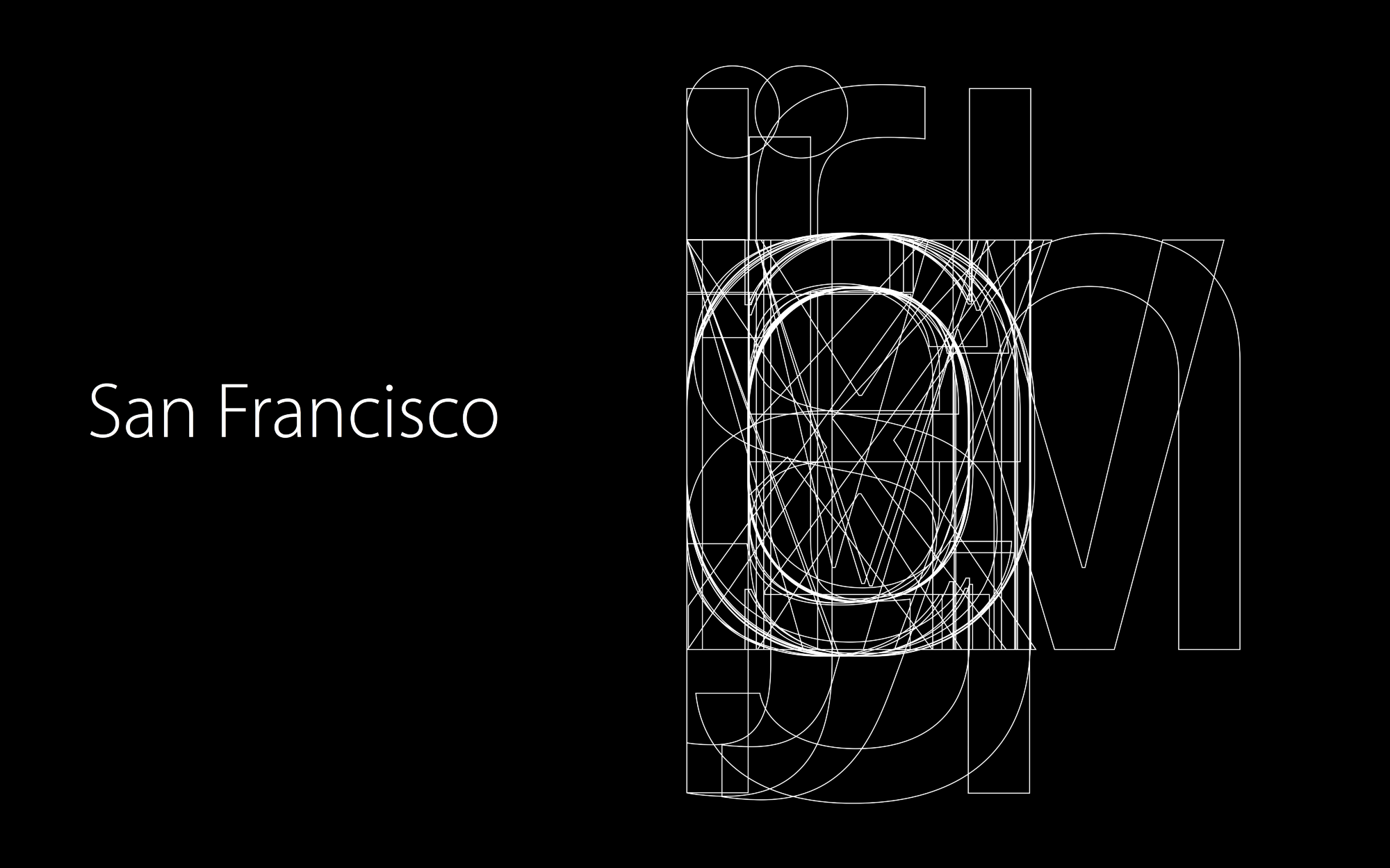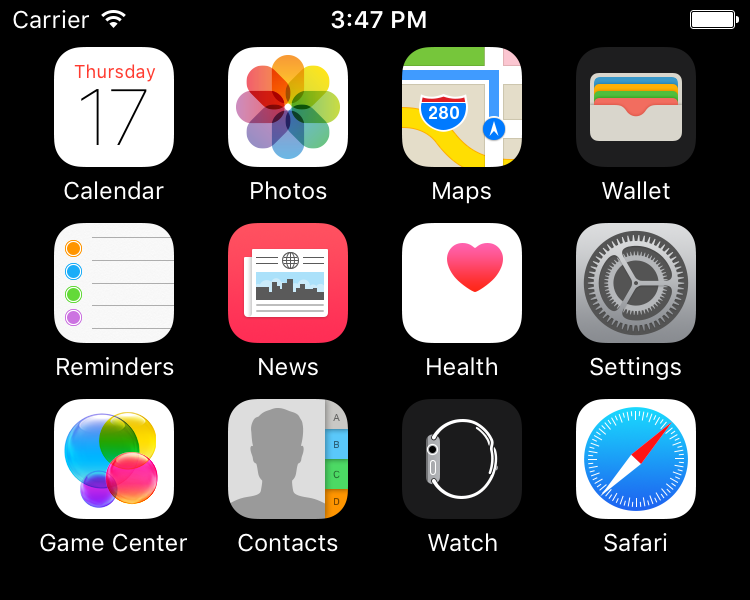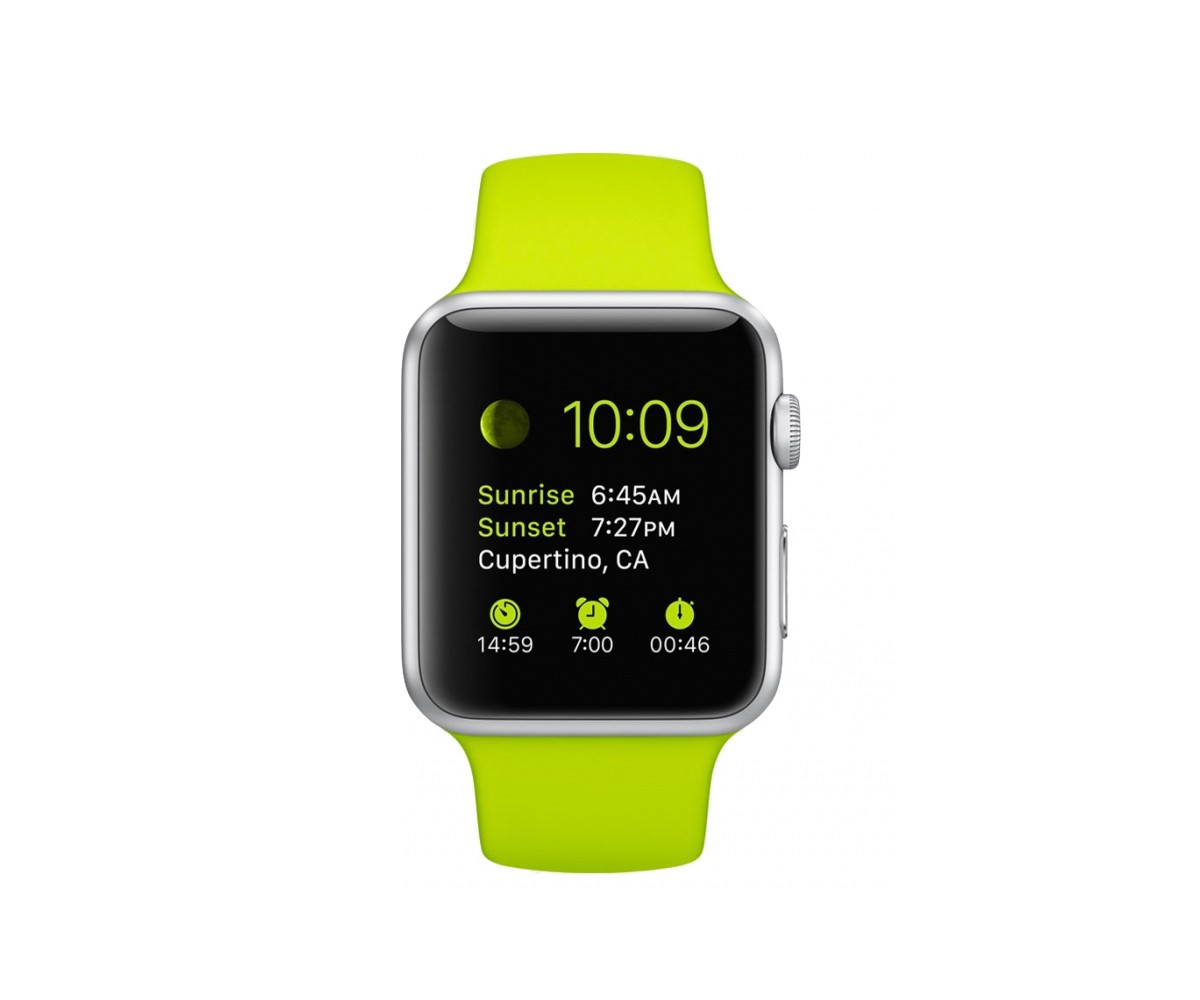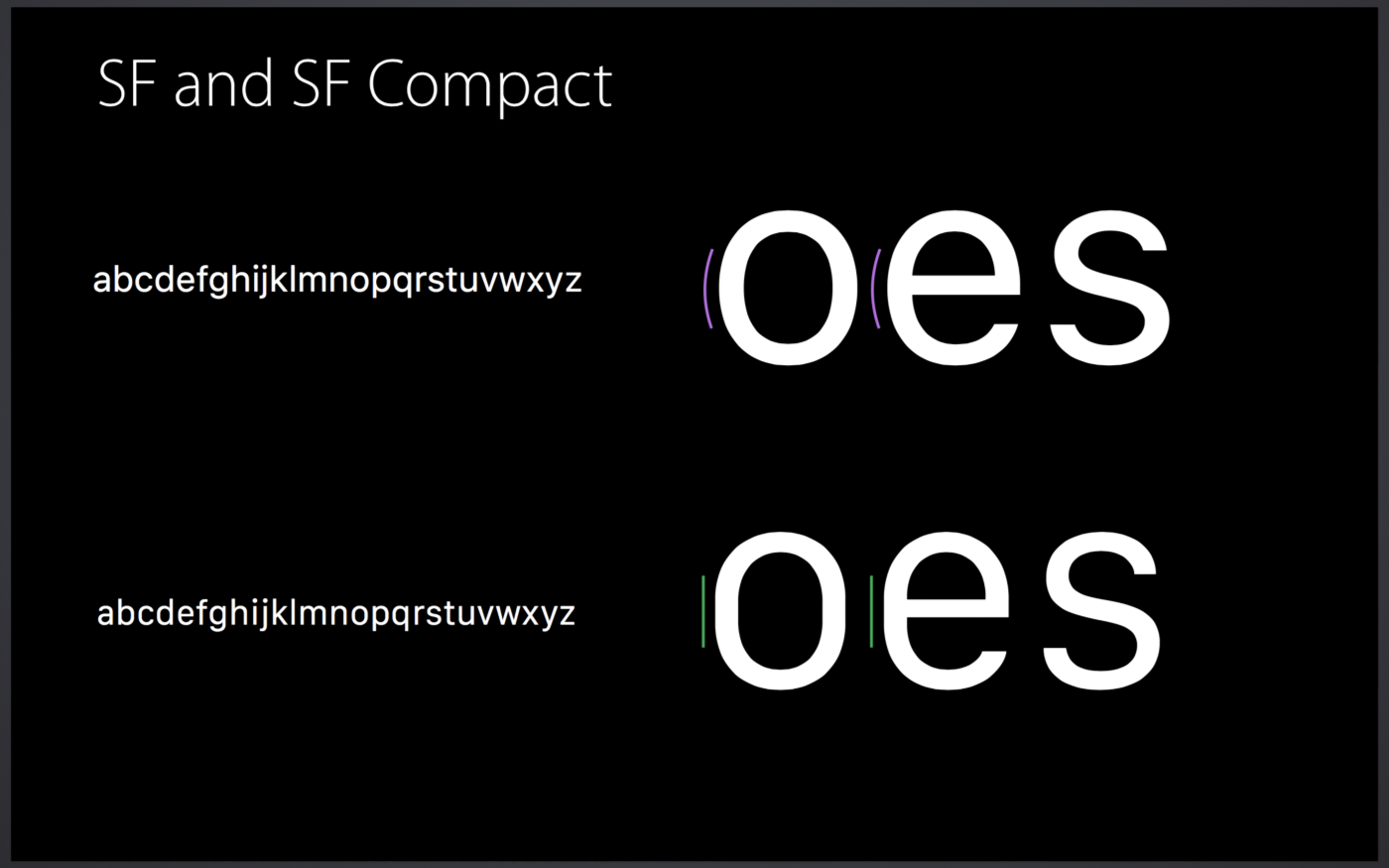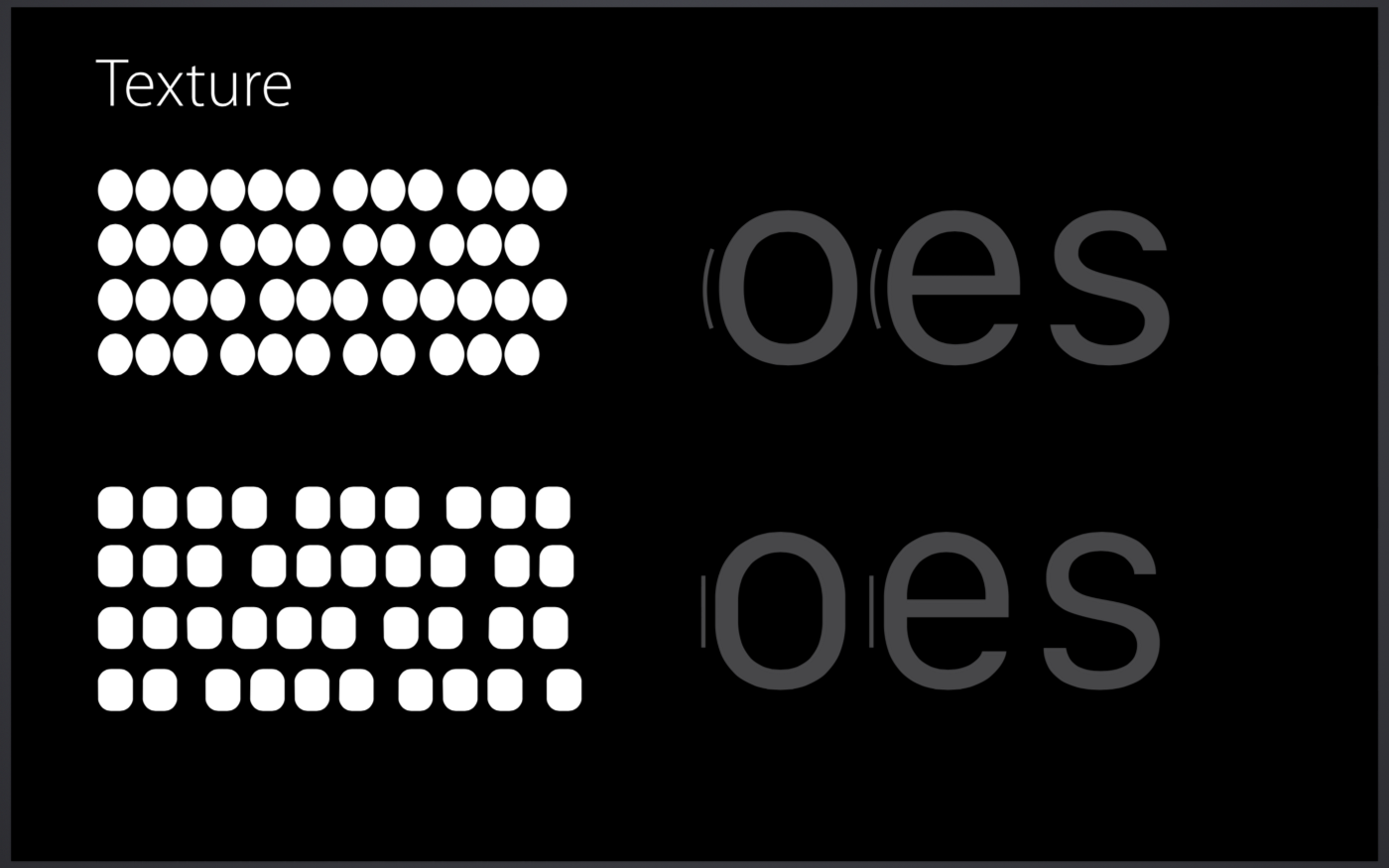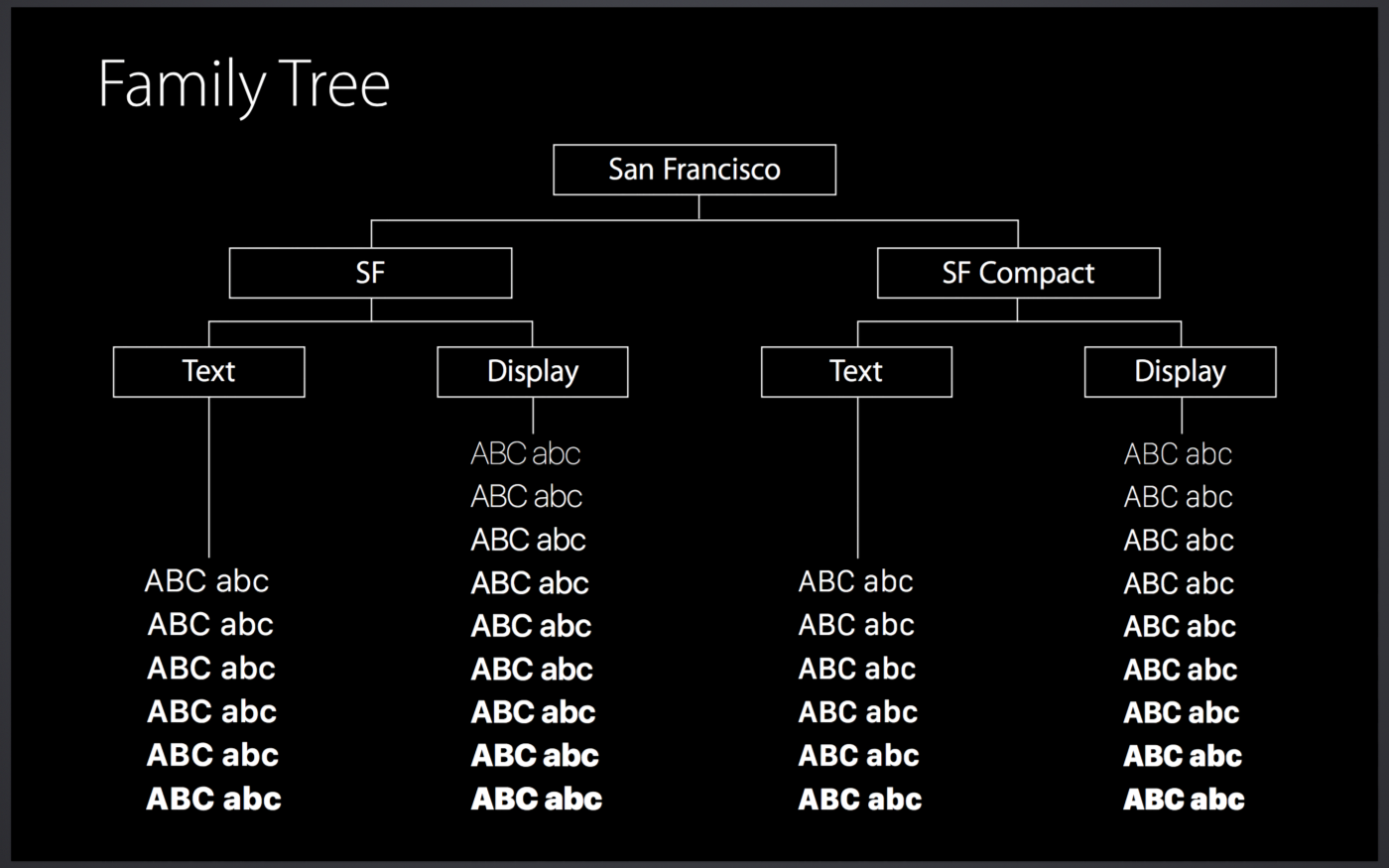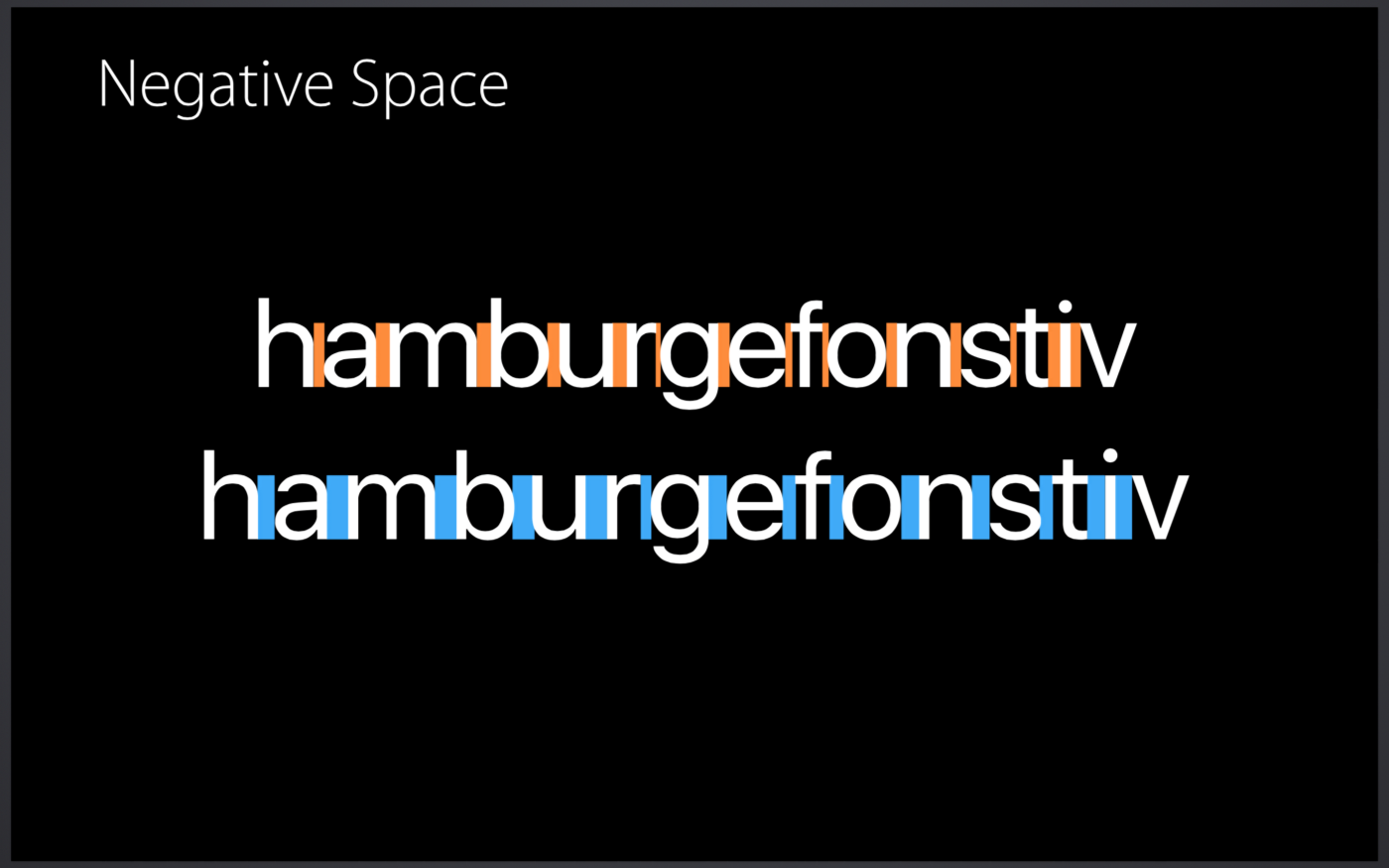
iOS 9如今已公开发布。带来了一些细微的变化,但iOS 9的系统字体变成了苹果新推出的旧金山字体,代替了之前用的Helvetica Neue。
Helvetica(左),旧金山字体(右)
旧金山字体之前已经用于Apple Watch中,如今则成为苹果全平台的统一字体:Apple Watch、iPhone、iPad和Mac。
Apple Watch
从第一台iPhone起,苹果就将Helvetica当作系统字体。而且从10.10 Yosemite开始,Mac OS X系统的字体也从Lucida Grande改为了Helvetica。苹果为何抛弃Helvetica?它是全世界最著名最受欢迎的字体。
小字号Helvetica太纤弱
据说Helvetica不适合小字号使用。当Mac OS X Yosemite系统字体改为Helvetica,许多设计师声称Helvetica并不合适。
“Helvetica糟糕透了”,Erik Spiekermann说
如果你输入小字号的Helvetica文字,你会发现易读性很低,显得模糊。有些文字交叠在一起,难以辨识。据说苹果设计出旧金山字体正是为了让小号文字在Apple Watch上更易读。
小号字母交叠在一起
但如今,小屏幕设备分辨率比印刷品还高,iPhone中的文字并不像Apple Watch那么小。为什么苹果把iOS、Mac OS X的系统字体都改了,而不是只用于Apple Watch?
旧金山字体不仅仅是一款字体
旧金山字体拥有许多高度易读的特征。实际上Apple Watch和iOS/Mac上的旧金山字体并不相同。
字体族“SF”用于iOS/Mac,而“SF Compact”用于Apple Watch。在“o”、“e”这类圆形字母上可以看出区别。SF compact的竖线比SF更平坦。
SF与SF Compact
这点差异使得SF Compact的文字有更大的字距,从而使Apple Watch这样的小设备有较高的易读性。
而且,SF与SF Compact被划分为两套子字体族,分别称作“Text”和“Display”。这就是苹果所谓的“视觉尺寸”。Text字体用于更小的文字,Display字体更大。
旧金山字体族
正如我之前提过的,Helvetica这种非自然(或者说无衬线)字体,两个邻近字母会“交叠”在一起,像“a”、“e”、“s”这种字母在小字号时看起来很相似。
Display与Text字体
用于小号字的旧金山Text字体,被设计成比Display字体有着更大的字距。Text字体的字怀也更大,为了小屏幕的易读性。
旧金山字体是动态的
旧金山字体的一大特点是它动态组织文字。系统会随着字号自动切换Display/Text字体。明确地说,20pt正是这个界限。
设计师与开发者不用操心该用哪种字体。比如给UILabel设置系统默认字体,系统就会为你选择合适的文字。
旧金山字体有一点让我印象很深,就是它的冒号(:)的显示方式。一般情况,冒号会刚好放置在基线上,所以放在数字之间时,它并非垂直居中的。而旧金山字体中,会自动将它垂直居中对齐。
垂直居中的冒号
旧金山字体是为数字时代而生的字体
如你所见,旧金山字体经过了精心的设计,为了使任何字号、任何设备都易于阅读。
被旧金山字体所替代的Helvetica,1957年诞生于瑞士,那时尚没有电子设备。即使今天,Helvetica也被许多公司作为企业字体广泛运用,毫无疑问,未来它会被当作一款伟大的经典字体使用。
另一方面,旧金山字体是一款现代字体。它会根据环境动态改变文字。这是数字时代的一种“数字原住民”字体。